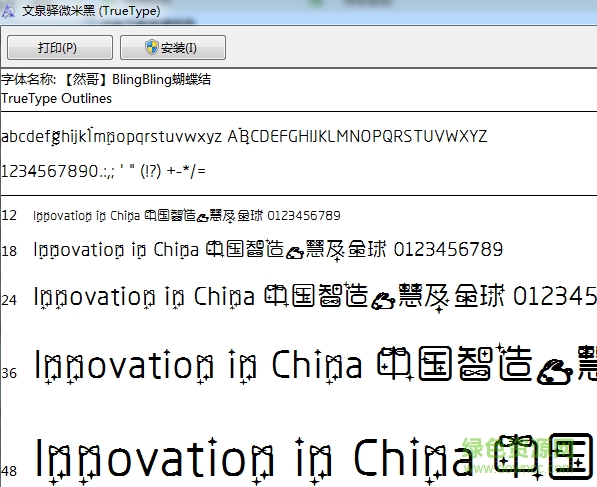
戀愛蝴蝶結(jié)字體是一款超好用的中文個性字體,字體中穿插的可愛蝴蝶結(jié)極大的滿足的女人的少女心,對于平面設(shè)計來說,非常適用于女士的廣告設(shè)計,需要的用戶就趕快來綠色資源網(wǎng)免費下載收藏吧!
戀愛蝴蝶結(jié)字體是一款極具個性的字體,該字體十分飄逸,彰顯了自己的個性,有喜歡的朋友可以來綠色資源網(wǎng)下載使用!